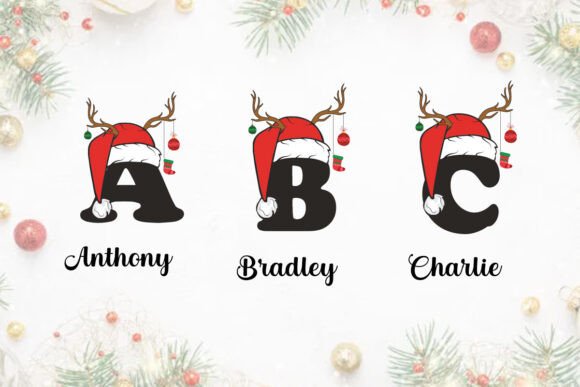
Christmas Alphabet Letters Sublimation
Поиск подходящих элементов дизайна может быть сложным, но Christmas Alphabet Letters Sublimation предлагает исключительную коллекцию, которая мгновенно улучшит вашу работу.